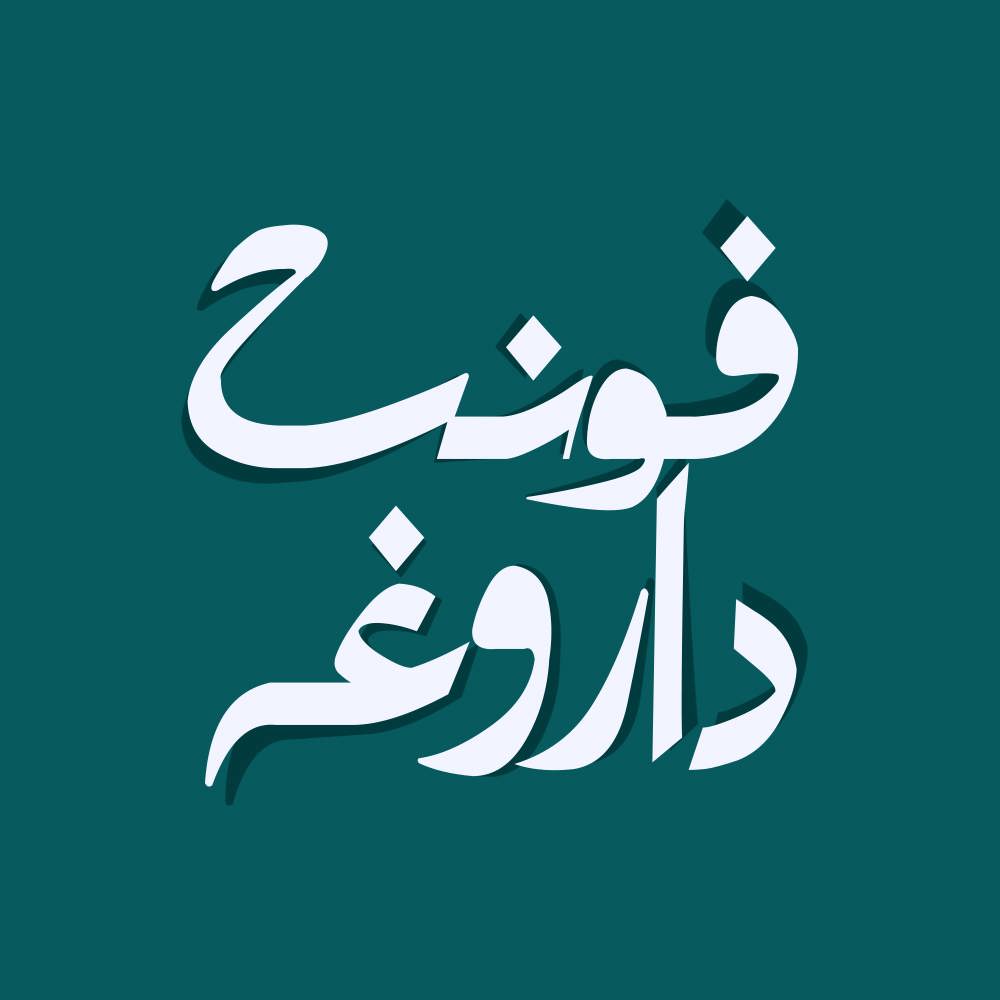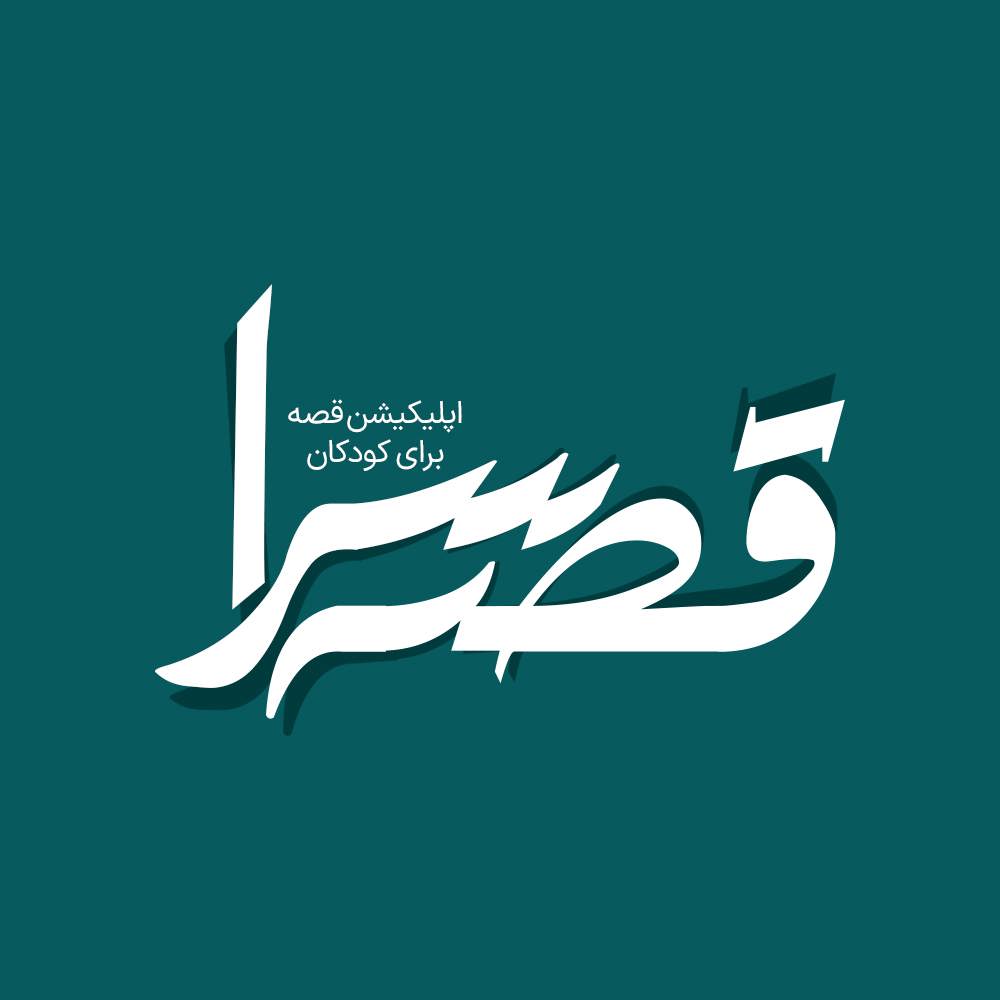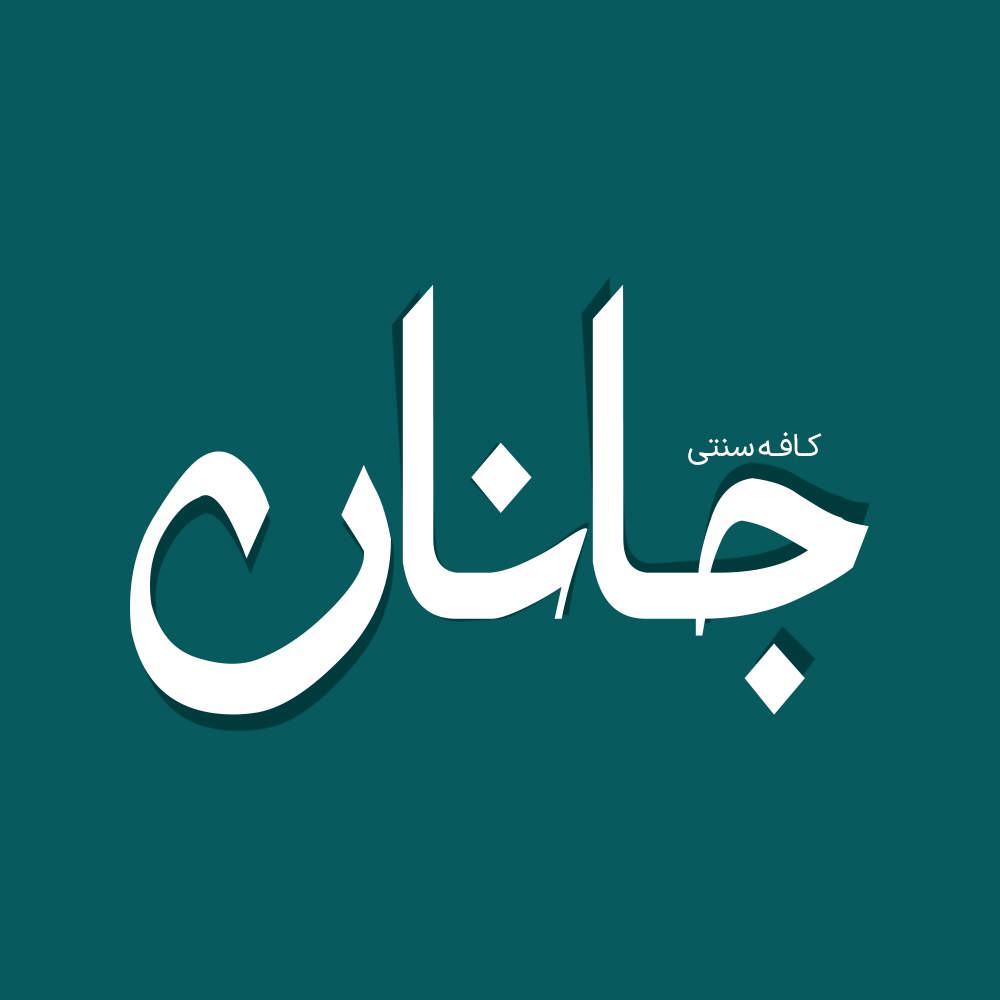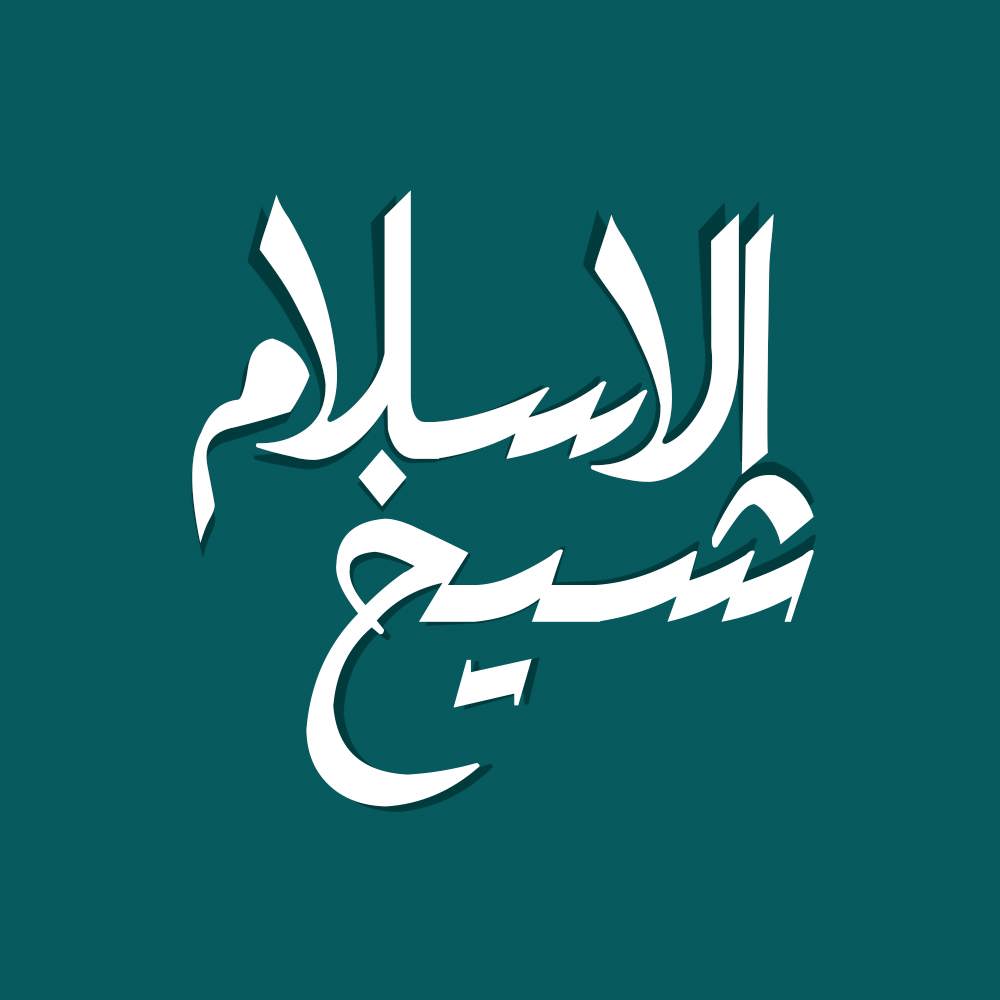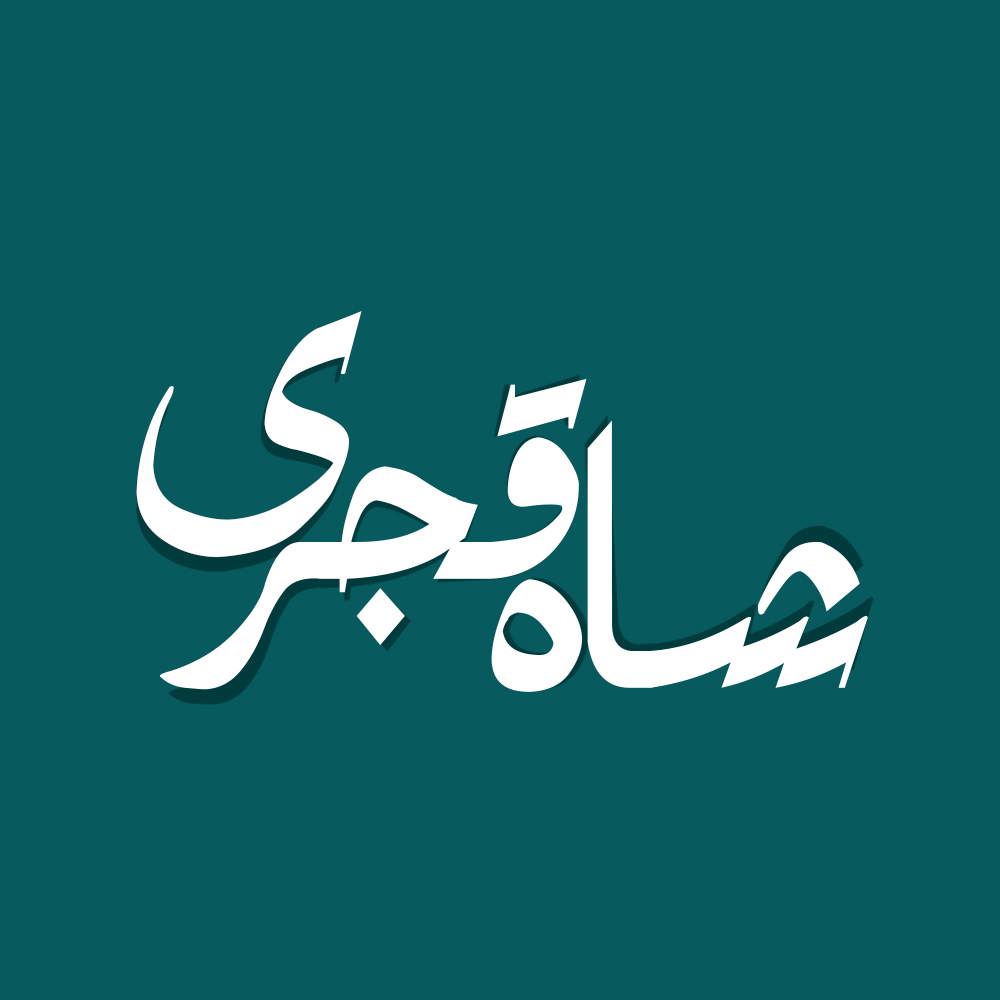
فونت فارسی داروغه Darughe Font
فونت فارسی داروغه یک فونت نمایشی با شخصیتی جسور، خلاق و مستحکم است. فونت جدید داروغه با الهام از سبکهای سنتی ایرانی و ترکیب آن با مدرنترین المانهای طراحی گرافیکی ساخته شده است و برای طراحان گرافیک، تولیدکنندگان محتوا، تایپوگرافی و طراحی لوگو انتخابی بینظیر میباشد. فونت داروغه با حالوهوای قدیمی خود، حس خاطره و نوستالژی را تداعی میکند. وقتی کاربر متنی را با این فونت میخواند، به یاد تابلوهای قدیمی شهر، پوسترهای فرهنگی و حتی کتابهای درسی گذشته میافتد. همین ویژگی باعث میشود طراحی شما متفاوت، احساسی و ماندگار شود. در ادامه برای شما نمونه تایپ های این محصول حرفه ای رو آماده کردیم که میتونید مشاهده کنید.
- طراحی لوگوهای خاص با هویت ایرانی
- تایپوگرافی و پوسترهای فرهنگی و هنری
- جلد کتاب و مجله با حس نوستالژی
- طراحی بنر تبلیغاتی و شبکههای اجتماعی
- استفاده در برندینگ برای نمایش اصالت و اعتماد
پیشنمایش و نمونه تایپ های فونت داروغه